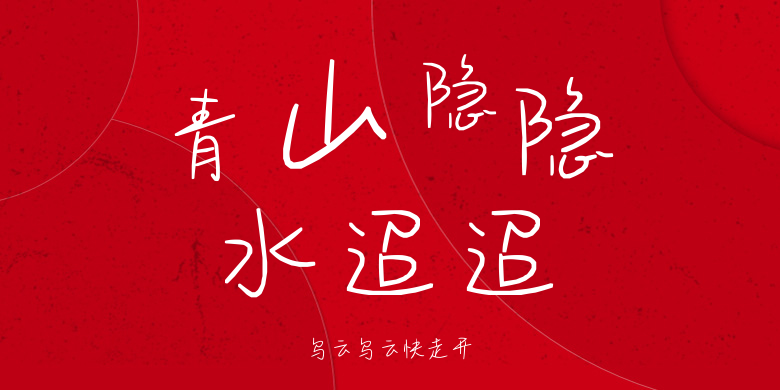
乌云乌云快走开
乌云乌云快走开,这款字体结构工整、笔画清晰,兼顾美观与易读性,适用于标题、正文、海报、包装、LOGO 等多种场景。字形优雅稳定,风格百搭耐看,适配日常排版与创意设计,让文字呈现更舒适、更具质感。乌云乌云快走开一笔一画,皆是细节,以均衡的比例、流畅的线条打造舒适视觉体验,字形端正大气,风格简约现代。无论是商业设计、品牌宣传还是日常排版,都能轻松驾驭,让文字更有格调与力量。乌云乌云快走开字体下载。